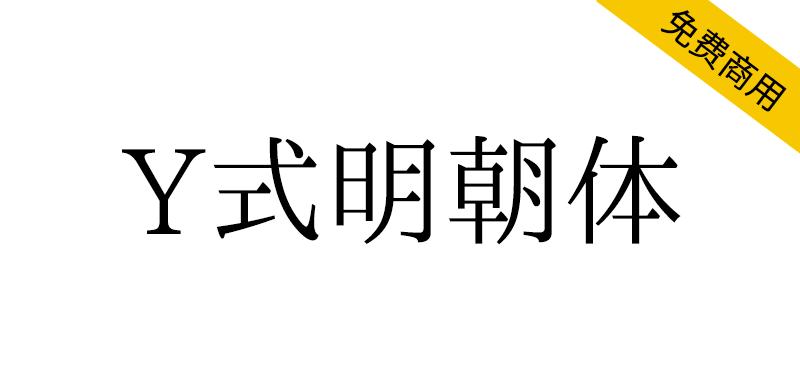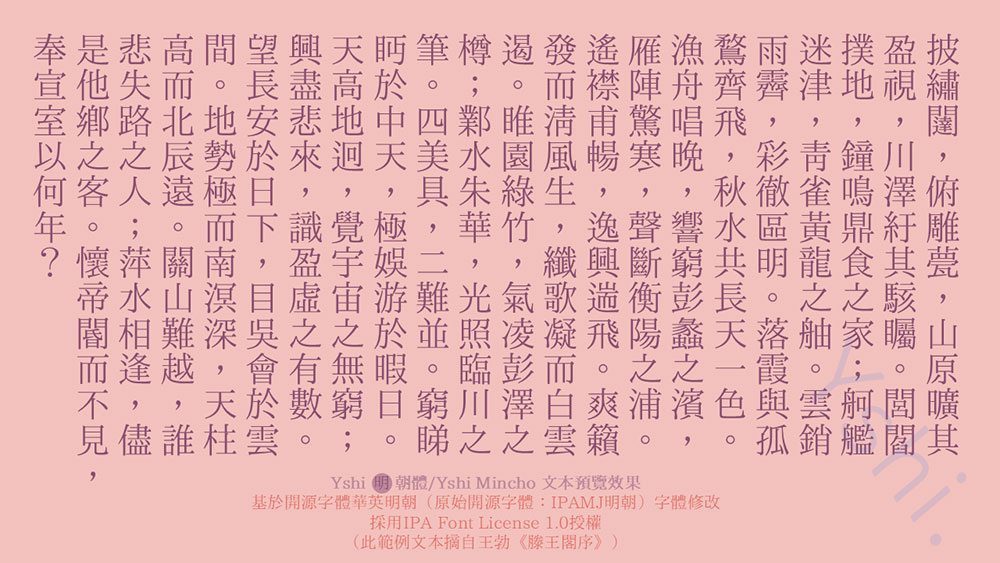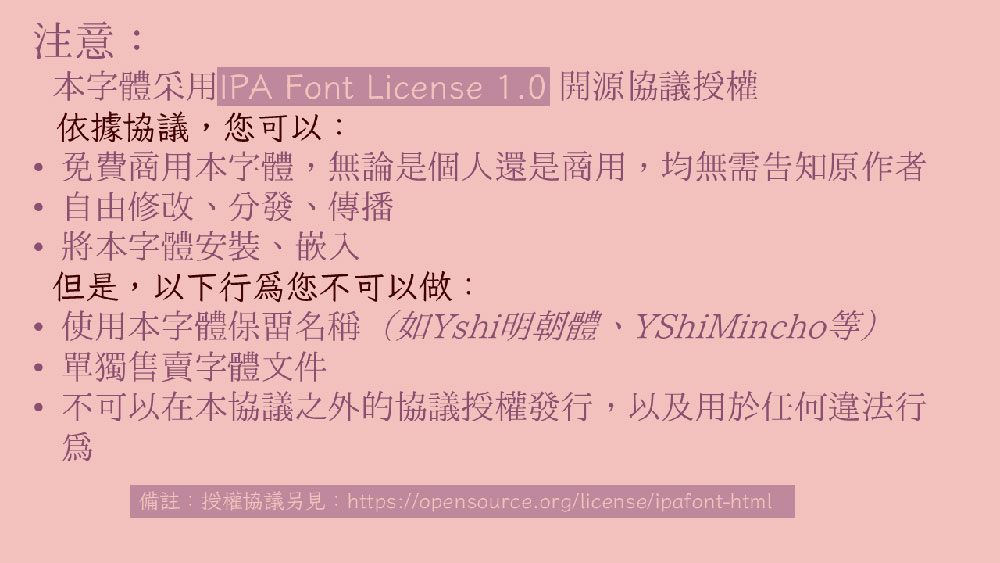
Y式明朝体(Y式宋体 / YShiMincho)是基于华英明朝、 IPAmj明朝 ,并借用一点明朝,修改的中文开源字体,字体以传统字形为主。
注意:1、本字体着重收录汉字区,至于符号区待定,2、个别简体字由于来自于一点明朝,字形可能较为奇怪,后续计划更改、版本分流等等,3、个别字由于现成部件没有合适的比例、或者缺乏现成部件,故有些字存在机械挤压而造成粗糙,由于本人技术有限,只能略微调整、使其勉强具有美感,4、本字体并不完全符合《传承字形推荐形体表》,系个人参照之并结合诸多流传的旧字形写法,根据个人喜好取舍之,5、不计划推出多字重,6、标点符号本项目默认居中。